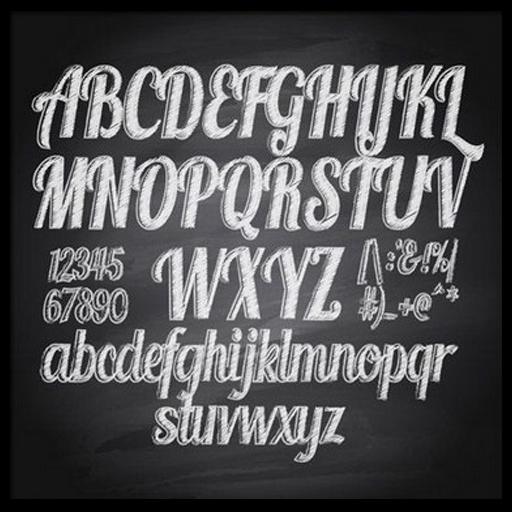
Рисовать мелом на доске онлайн
Chalk Text Effect — не совсем доска, просто выбираете понравившийся Вам шрифт и фон в виде зеленой, черной или любой другой мельной доски и пишите текст.
Результат получается довольно качественный, прямо как реальное фото. Но шрифты не поддерживают русских букв, так что подойдет только тем, кто хочет написать, что-то на английском.
Вот пример какая картинка у Вас может получиться.
Как сымитировать надпись мелом в фотошопе
Для оформления свадьбы потребовалась имитация доски с написанным мелом текстом. Эта доска стоит позади столика со сладостями и довольно большая. Вот образец того, на что нужно было ориентироваться. Первый шаг – погуглить. Из первого десятка результатов я выбрала два: результаты показались мне похожими на правду.
Я использовала в основном первый урок. Одно маленькое но – если делать все в точности как в уроке, получается совершенно не то, что изображено на картинках – как будто у автора был свой собственный фотошоп. Пришлось импровизировать =)
Фон доски в уроке – зеленоватый. Мой пример требовал черного фона. Поэтому вложенную в пример поверхность я увеличила в размерах до нужных мне 2 метров в ширину, убрала фильтром пикселизацию, снизила насыщенность до -100 и яркость до -50. Получилась вполне себе черная поверхность с царапинами.
Саму форму надписи я создала в иллюстраторе и вставила в фотошоп в виде смарт-объекта. Это позволило вносить правки в векторную часть и сразу видеть результат на доске. Выглядит довольно страшненько – это всего лишь основа для нанесения.
Самое сложное – кисть для рисования «мела». Даже выставив все настройки один в один, показанного автором на картинке результата у меня не получилось. Погоняв ползунки туда-сюда, я нашла нечто, напоминающее мел при шваркании планшетом с учетом нажима. На картинке настройки моей кисти.
Дальше автор предлагает довольно хитрую и быструю методику рисования мелом.
Но она хорошо подходила а) для его кисти и б) для букв одной толщины. У меня ни того, ни другого =) Поэтому я отключила векторный слой, задала по нему выделение и дальше планшетом и тонкой кистью с прозрачностью 100% написала все буквы. Заданное выделение по периметру рисунка не давало мне выйти за границы букв.
Получилось даже лучше – так как каждая буква рисовалась руками, они все вышли немножко разными. Для большей достоверности я еще немного покорежила сами буквы в иллюстраторе, чтобы одни и те же буквы выглядели чуть по-разному.
Уроки редко получается просто скопировать. Но если их адаптировать, можно найти много полезных советов. А вы часто пользуетесь уроками с интернета? И насколько успешно?
Создаем в фотошопе текст, написанный мелом на школьной доске | DesigNonstop
Создаем в фотошопе текст, написанный мелом на школьной доске
Сегодня попробуем сделать зеленую школьную доску и написать на ней мелом текст. Как всегда, за идею урока спасибо Vectips, который реализовал ее в иллюстраторе. Я же ее воплотила в жизнь с помощью фотошопа. В этом уроке есть несколько любопытных простых приемов, которые дают потрясающий эффект. Сначала поколдуем над доской, придав ей немного потертый вид в прямом и переносном смысле. Потом напишем текст и с помощью режима наложения «Растворение» (Dissolve) будем добиваться эффекта надписи, сделанной мелом. Потом немного украсим надпись.